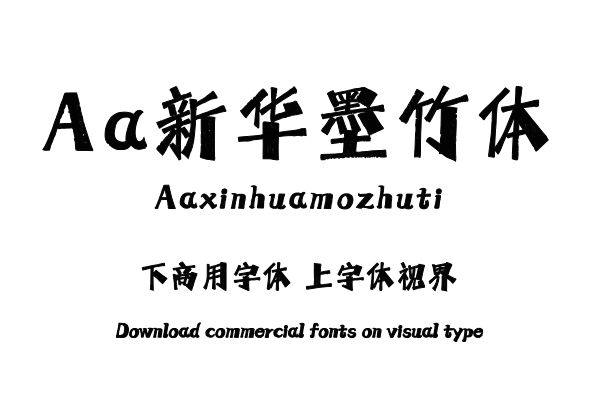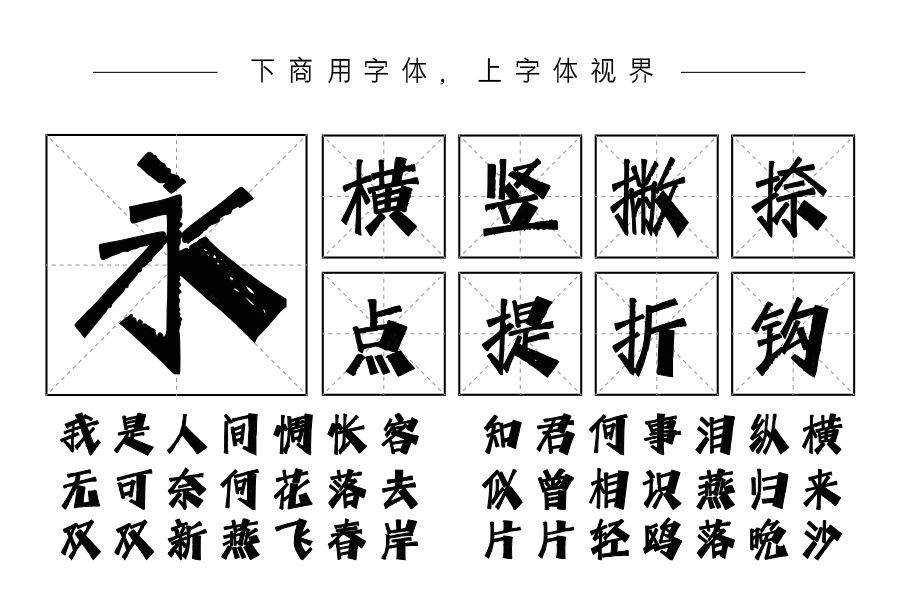
结合书法艺术与现代字体技术设计一款创意标题字体,以丰富字体产品风格,迎合各类商业设计需要。笔画虽为毛笔书写却如竹子一样笔直,粗细笔画对比倾斜,粗笔画内呈现斑驳的......购买须知:“下载服务费”与“字体VIP”所获得字体 仅用于个人非商用, 商用请联系付费授权。本字体为电脑用字,手机没有root权限不支持直接手机换字(手机如何root,请自行百度搜索教程)。购买前请先 了解清楚后再付款 ,字体为虚拟产品无法回收 一旦购买不支持退款。